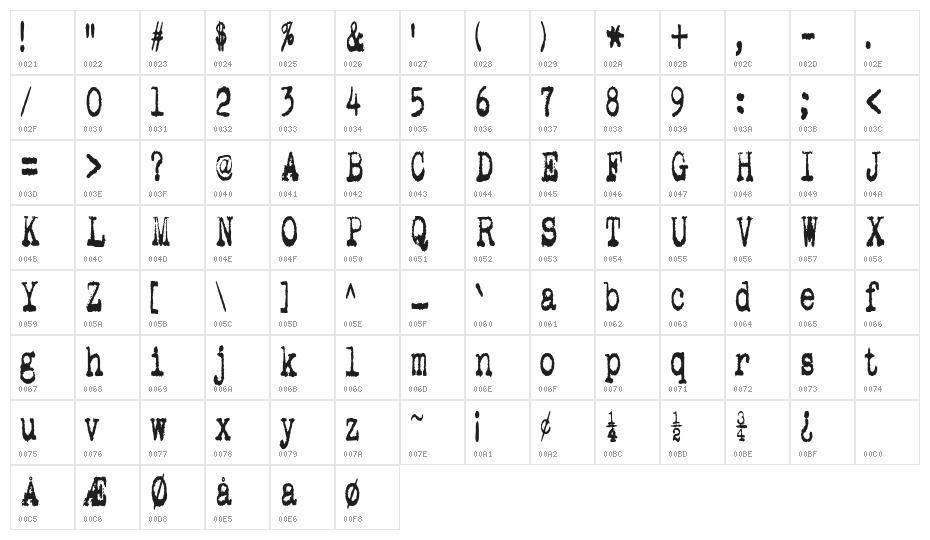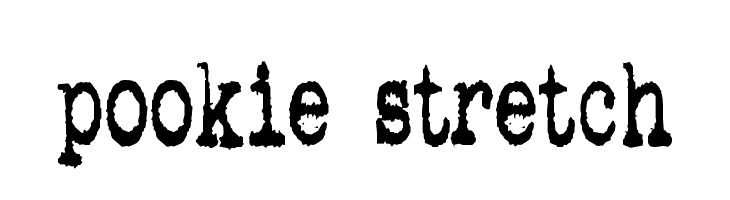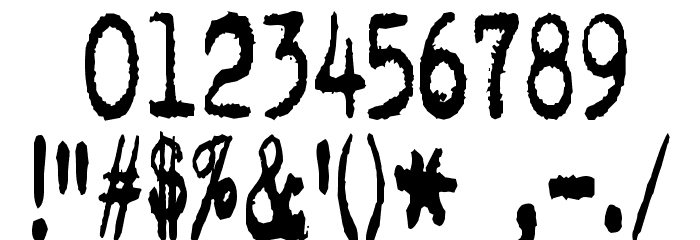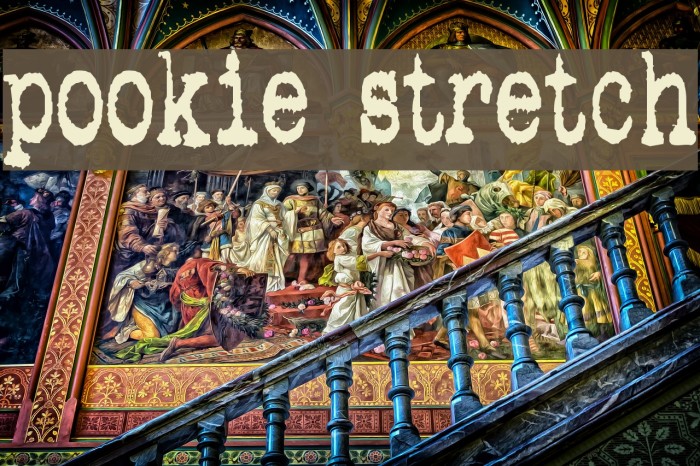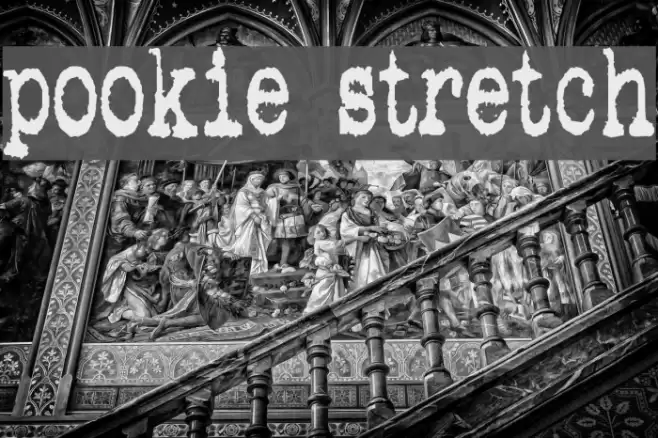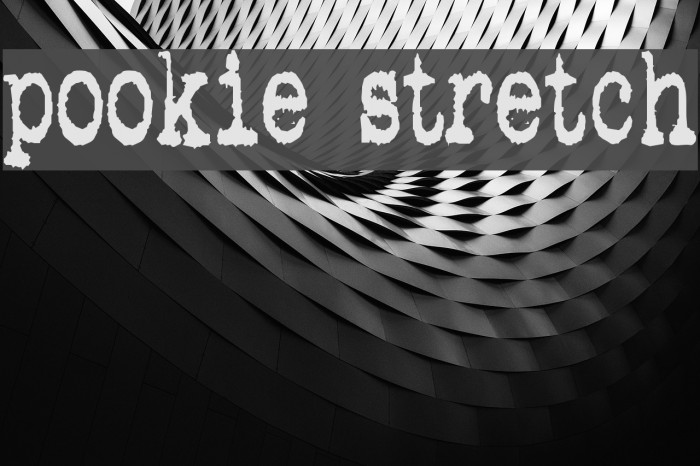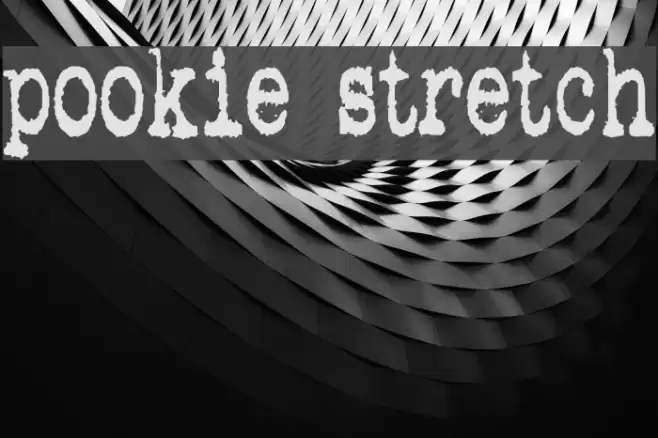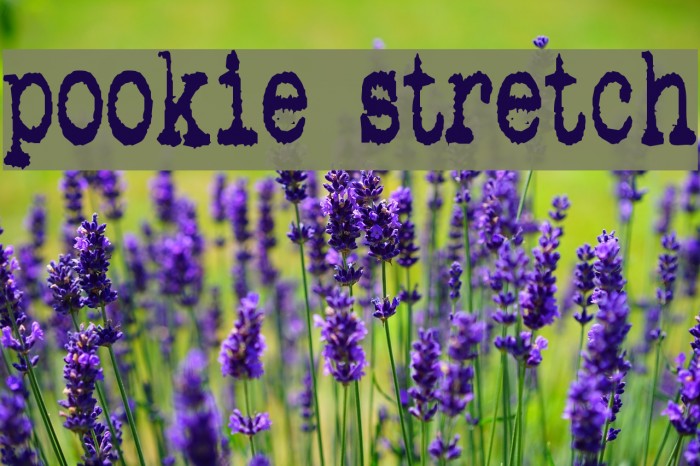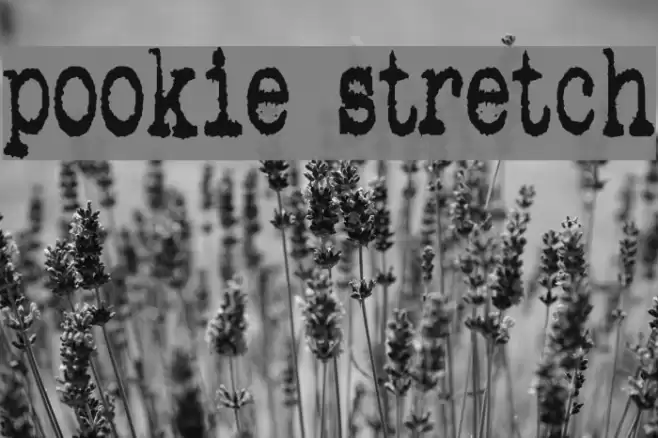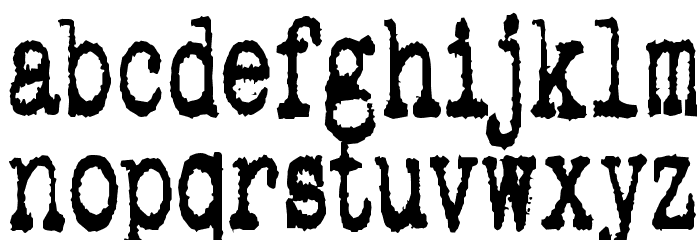
pookie stretch Font
✎ Typewriter
| カテゴリ | Typewriter |
| 幅 | Expanded |
| おすすめプロジェクト | Ideal for projects requiring a vintage or grunge aesthetic, such as posters, album covers, or branding for artisanal products. |